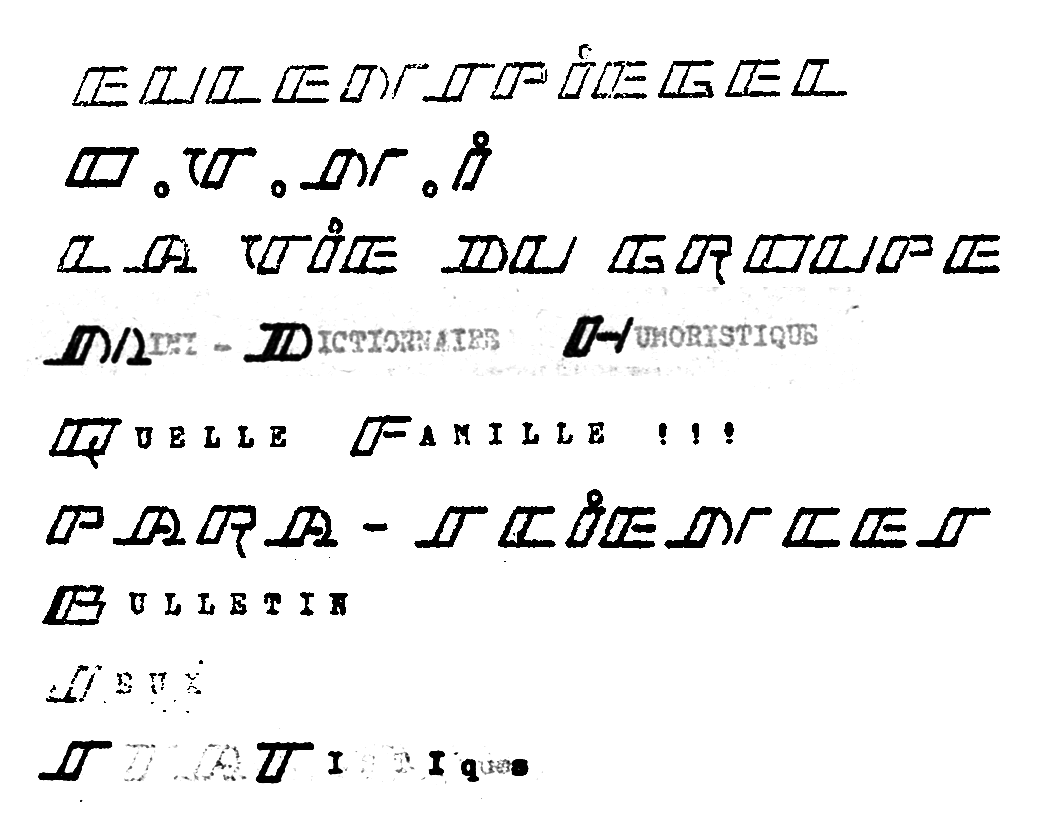
Le 05/05/2012 13:30, Jean-Luc BLARY a écrit :
J'ai retrouve 21 lettres sur 26 (manquent K, W, X, Y et Z – je me souviens en avoir "dessiné", mais apparemment uniquement pour le compte de l'armée).Le 05/05/2012 13:23, Jacques André a écrit :Par ailleurs, pendant mon service militaire, les secrétaires (AFAT) utilisaient tout un alphabet normalisé pour faire les entêtes des Notes de Service, avec N et S dactylographiés avec des / , des - et autres ). SI quelqu'un avait trace du modèle de cet alphabet, ça m'intéresserait ! Merci.À l'armée, mon "arme de service" étant la machine à écrire (1), j'ai rédigé nombre de rapports ainsi titrés. J'ai encore des exemples de tout l'alphabet qu'on composait de cette manière. Dès que j'ai un moment, j'exhume ça.
Désolé pour la qualité, il s'agit de scans de pages en couleur faites au duplicateur à alcool vieilles de 38 ans, j'ai rattrapé autant que possible.